Một yếu tố quan trọng ảnh hưởng đến readability đó chính là việc chọn một kiểu chữ rõ ràng. Đây cũng sẽ là bước khởi đầu cho một bài viết hấp dẫn.
[quote]Yếu tố nào tạo nên một kiểu chữ rõ ràng?[/quote]
Khi đọc, chúng ta không nhìn vào từng chữ cái, mà nhìn (hoặc đọc) hình dạng của những từ ngữ. Những hình dạng ấy được tạo nên từ hai yếu tố cơ bản: đường nét của các con chữ và khoảng cách giữa các chữ cái. Vậy nên tính rõ ràng sẽ không tồn tại được nếu không có hai yếu tố này.
Bạn có bao giờ thử đọc một văn bản đã trải qua nhiều lần photocopy? Kinh nghiệm cho thấy kiểu chữ sẽ trở nên khó đọc hơn sau mỗi lần in lại. Vậy tại sao điều đó lại xảy ra? Nhiều lần in lại sẽ làm cho bản in trở nên sáng hơn. Các nét thanh dường như biến mất, chỉ để lại một phần của các chữ cái và phá hỏng hình dạng của những từ ngữ. Hoặc nhiều lần in lại sẽ khiến những đường nét trong bản in trở nên nhỏ hơn. Khoảng trống bên trong và xung quanh các chữ cái sẽ dần biến mất. Đường nét và khoảng trống của các chữ cái mất dần sẽ làm thay đổi tính rõ ràng của bản in, điều này sẽ gây rất nhiều khó khăn cho người đọc.
Web typographer cần chú ý đến các đường nét và khoảng trống trong kiểu chữ vì độ phân giải của màn hình. Có rất nhiều trường hợp đường nét và khoảng trống nhỏ có thể biến mất, như trong ví dụ về photocopy ở trên, điều đó khiến văn bản trở nên khó đọc hơn.
[quote]So sánh giữa Georgia và Helvetica[/quote]
Một kiểu chữ đơn giản sẽ dễ đọc hơn trên màn hình vì một số vấn đề về độ phân giải. Thật ra là chưa hoàn toàn đủ.
Helvetica đơn giản và rõ ràng hơn Georgia. Tuy nhiên, những văn bản sử dụng kiểu Helvetica thì lại không dễ đọc, thậm chí nó trông có vẻ nhỏ hơn kiểu Georgia và là một kiểu chữ phức tạp hơn. Tại sao?
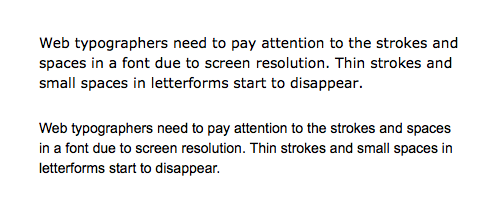
Georgia, của nhà thiết kế kiểu chữ Matthew Carter, được thiết kế cho việc đọc trên màn hình. Trong các điều khoản khi in, nó có một x-height tốt mà không làm mất phần ascenders và descenders. Nó cũng có một apertures mở, terminals dễ nhìn và những khoảng trống rõ ràng hơn Helvetica. Tôi sẽ chỉ rõ những phần dưới đây.
[quote]Điều khoản khi in[/quote]
Baseline là đường bên dưới các chữ cái
Descenders là đường nét của chữ cái kéo dài phía dưới Baseline.
Descenders của Helvetica và Georgia đều có cùng độ dài nhưng serifs của Georgia giúp descenders của nó rõ ràng hơn
Serifs là một nét ngang nhỏ, thường kết thúc ở phần trên hoặc dưới cùng của stem – một nét dọc trong chữ cái.
Georgia (trên cùng) là serif font (kiểu chữ có chứa serif), còn Helvetica (dưới cùng) là san serif font (kiểu chữ không chứa serif)
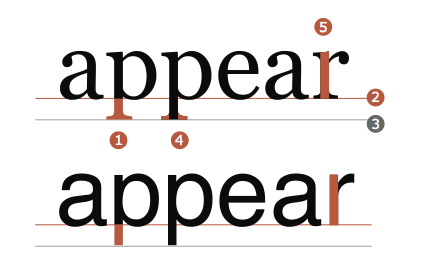
Ascenders là nét kéo dài lên phía bên trên đường meanline – một đường kẻ vô hình chạy dọc theo phần trên cùng của chữ in thường.
Meanline đánh dấu x-height của kiểu chữ – chiều cao của các chữ in thường giữa baseline và meanline.
Georgia có ascenders dài hơn Helvetica. Các ascenders rộng rãi đó giúp Georgia trông rõ ràng hơn ( Hãy chú ý rằng chữ “t” và “ f” trong Helvetica nhìn rất giống nhau). Bù lại phần dài hơn của ascenders, Georgia có x-height ngắn hơn. Thật đáng tiếc khi x-height ngắn hơn đó đã làm cho kiểu chữ trong nhỏ hơn (ngay cả khi cùng kích thước với Helvetica), nhưng điều đó vẫn đáng để có được ascenders dài hơn.
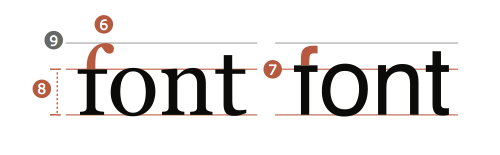
Aperture là các phần mở đầu của các chữ cái như “a” và “e”
Terminals là phần kết thúc của các nét không giới hạn bởi serif
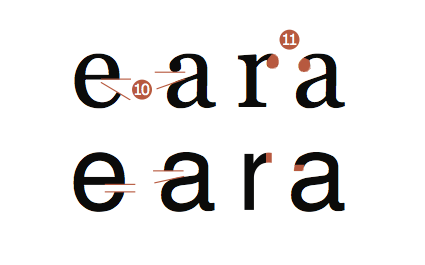
[quote]So sánh các kiểu chữ an toàn cho web[/quote]
Helvetica thực chất không phải là những kiểu chữ an toàn cho web. Helvetica nổi tiếng với sự đơn giản và rõ ràng của nó, nó tạo nên một kiểu chữ hoàn hảo cho thấy rằng rõ ràng và đơn giản chưa đủ để đảm bảo tính rõ ràng của một văn bản đọc trên màn hình.
Tiếp theo tôi sẽ so sánh Georgia với Times New Roman, và Verdana với Arial. Cả bốn đều là kiểu chữ an toàn cho web thích hợp với phần lớn máy tính.
Georgia và Verdana là những kiểu chữ rõ ràng hơn cho các văn bản trên web. Chúng được thiết kế để được đọc dễ dàng trên màn hình.
Số lượng những kiểu chữ có sẳn cho web typographers ngày càng tăng. Là một typographer bạn nên biết cách nhìn và nghĩ về một phần của những chữ cái để có thể tìm ra được những kiểu chữ rõ ràng khác ngoài Georgia và Verdana.
[quote]Times New Roman vs Georgia[/quote]
Times New Roman là một kiểu chữ nhỏ hơn Georgia. X-height của mỗi kiểu chữ gần như bằng nhau tại kích thước này, điều đó cho bạn thấy một điểm khác biệt rõ ràng.
Times New Roman có bowls (vòng tròn trong các chữ cái in thường) hẹp hơn so với Georgia. Điều đó dẫn đến một counterforms nhỏ hơn (khoảng trống không có letterform). Counterforms nhỏ hơn là điều mà các văn bản đọc trên màn hình thường đánh mất.
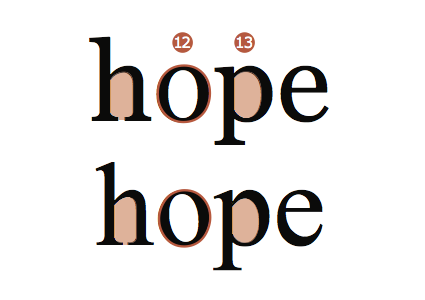
Times New Roman cũng có những nét đậm đậm hơn và những nét thanh mảnh hơn so với Georgia. Những nét thanh thường có xu hướng biến mất trên màn hình khi sử dụng kiểu chữ này cho văn bản. Xu hướng này kết hợp với bowls hẹp hơn làm cho văn bản giống như tập hợp những đường kẻ dọc. Người đọc phải tập trung nhiều hơn để đọc được các con chữ trong kiểu chữ Times New Roman.
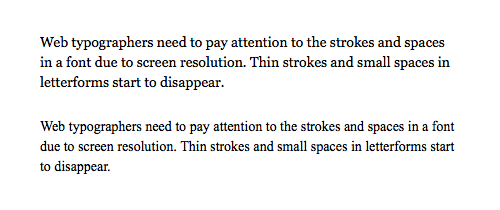
Đọc một văn bản (14 đến 16px) sẽ dễ dàng hơn nếu kiểu chữ của nó đáp ứng các yêu cầu:
- X-height rộng
- Aperture mở rộng
- Ascenders và descenders nổi bật
- Khoảng trống nhỏ giữa các chữ cái
- Terminals dễ nhìn thấy